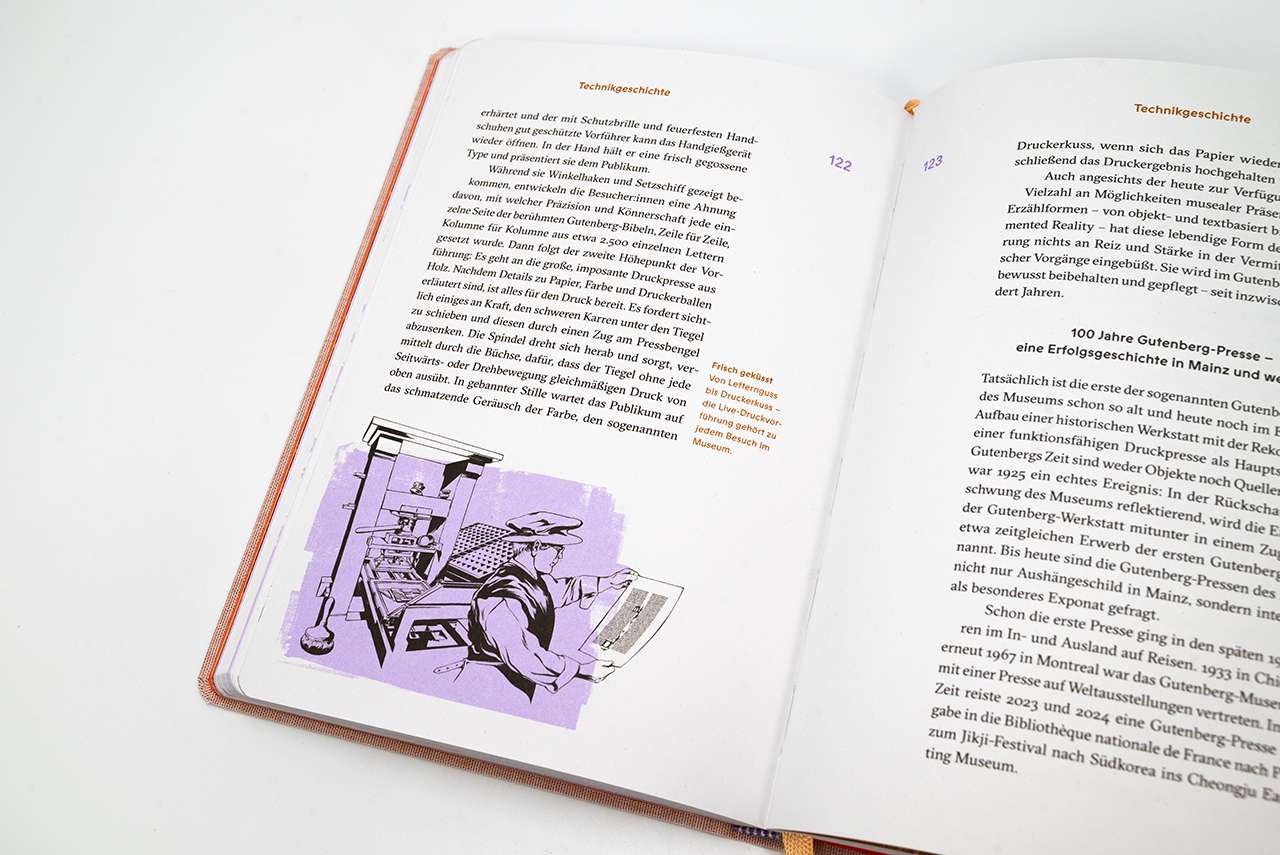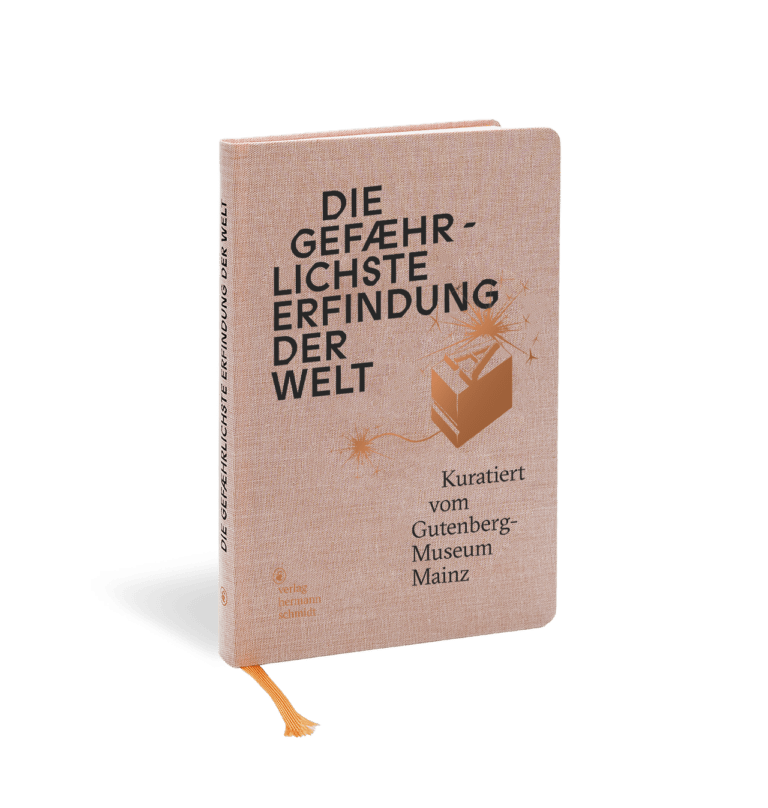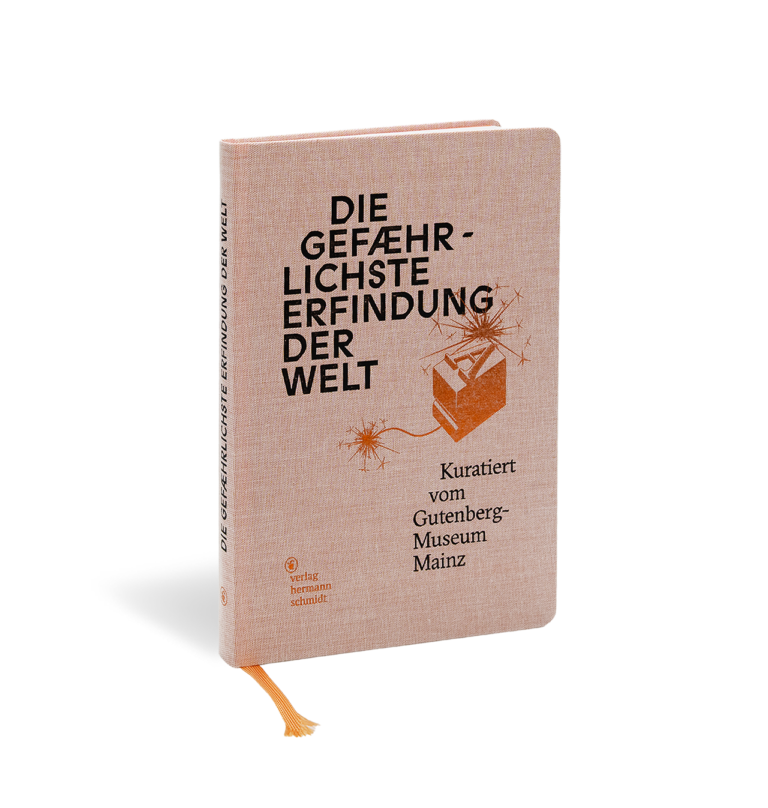
Die gefährlichste Erfindung der Welt – kuratiert vom Gutenberg-Museum Mainz
Man kann die Entwicklung des Druckens mit beweglichen Lettern als eine technische Meisterleistung des 15. Jahrhunderts sehen. Dann aber übersieht man das wirklich Wichtige an Johannes Gutenbergs Erfindung: die Folgen. Und die Wirkung.
Zur gefährlichsten Erfindung der Welt wurde das Drucken wegen seiner Wirkung auf Gesellschaften, die bis heute anhält: Das Drucken mit beweglichen, wiederverwendbaren Lettern in hoher Präzision, Geschwindigkeit und Auflage veränderte Machtverhältnisse, Autoritäten wurden hinterfragt, es beschleunigte Umbrüche, schaffte Öffentlichkeit und machte Bildung zugänglicher. Und es zwang Menschen, sich zu positionieren.
Es war – wie die digitale Revolution – ein disruptiver Vorgang mit ambivalenten Folgen.
Wer kontrolliert Information?
Wer trägt die Verantwortung für ihre Verbreitung?
Wer ist Gatekeeper des Wissens?
Wie unterscheiden wir zwischen Wissen und Meinung, Wahrheit und Täuschung?
Diese Fragen sind heute so aktuell wie vor 600 Jahren. Deshalb ist diese Einladung ins Gutenberg-Museum Mainz auch eine Einladung zur Auseinandersetzung mit Mediengeschichte und Mediennutzung, Meinungsbildung und Meinungsfreiheit und damit zum Nachdenken über Kernfragen der Zeit.
Ein Blick hinter die Kulissen
Zum 125-jährigen Jubiläum des Gutenberg-Museums in Mainz erlaubt dieses Buch einen Blick hinter die Kulissen: Wie entstand die Sammlung und wie wird sie für die Zukunft gesichert? Was erzählen die Objekte über die Vergangenheit und wie regen sie gleichzeitig dazu an, den heutigen Umgang mit Medien mutig zu diskutieren?
Das Buch zeigt auf, wie eine Erfindung im Laufe der Geschichte im Spiegel der aktuellen politischen und gesellschaftlichen Ereignissen immer wieder neu interpretiert und bewertet wird, wie eine Sammlung Fahrt aufnimmt und wie wichtig Kuratieren im Wandel ist. Museen befreien sich von der Vorstellung, reine Orte des Sammelns zu sein und verstehen sich mehr und mehr als Netzwerk, in dem sich Geschichte und Gegenwart begegnen und miteinander verweben. Digital und analog sind dabei keine Gegensätze, sondern ergänzen sich im didaktischen Interesse. Welche Verpflichtung geht für ein Museum aus den gesammelten Schätzen hervor? Wie lädt man vor Ort und digital über das Museum hinaus Menschen dazu ein, aktive Forschende zu werden? Und wie wandelt sich in einer Welt flacher Hierarchien die Rolle des Museums von Deutungshoheit zu Kooperation?
Die Demokratisierung des Kulturerbes
Mit dem veränderten Selbstbild wandelt sich auch die Art der Vermittlung: Das Museum versteht sich heute als ein Angebot zum Dialog auf Augenhöhe – und das über den physischen – im Entstehen begriffenen Ort hinaus. Je tiefer man in der Text eintaucht, umso neugieriger wird man sowohl auf die Interimspräsenz MOVED, als auch auf den im Bau befindlichen Neubau. So schließt das Buch nicht die Lücke zwischen Abriss, Interim und Eröffnung, sondern lädt zu Vorfreude und Nachdenken ein über eine große Erfindung und ihre weitreichenden bis in die Zukunft weisenden Folgen.
Zu Gestaltung und Ausstattung
Jörn Kaspuhl, einer der prägenden Editorial-Illustratoren gibt dem Buch mit seinen ausdrucksstarken Illustrationen und charakteristischen Bildbearbeitungen eine besondere Note. Katrin Schacke erfindet eine starke Typografie, die den prachtvollen Initialen der Gutenbergbibeln eine moderne Interpretation entgegenstellt.
Die gefährlichste Erfindung der Welt
Kuratiert vom Gutenberg-Museum Mainz
Gestaltung: Katrin Schacke
Das Buch erscheint aus Anlass des 125-jährigen Jubiläums des Gutenberg-Museums Mainz